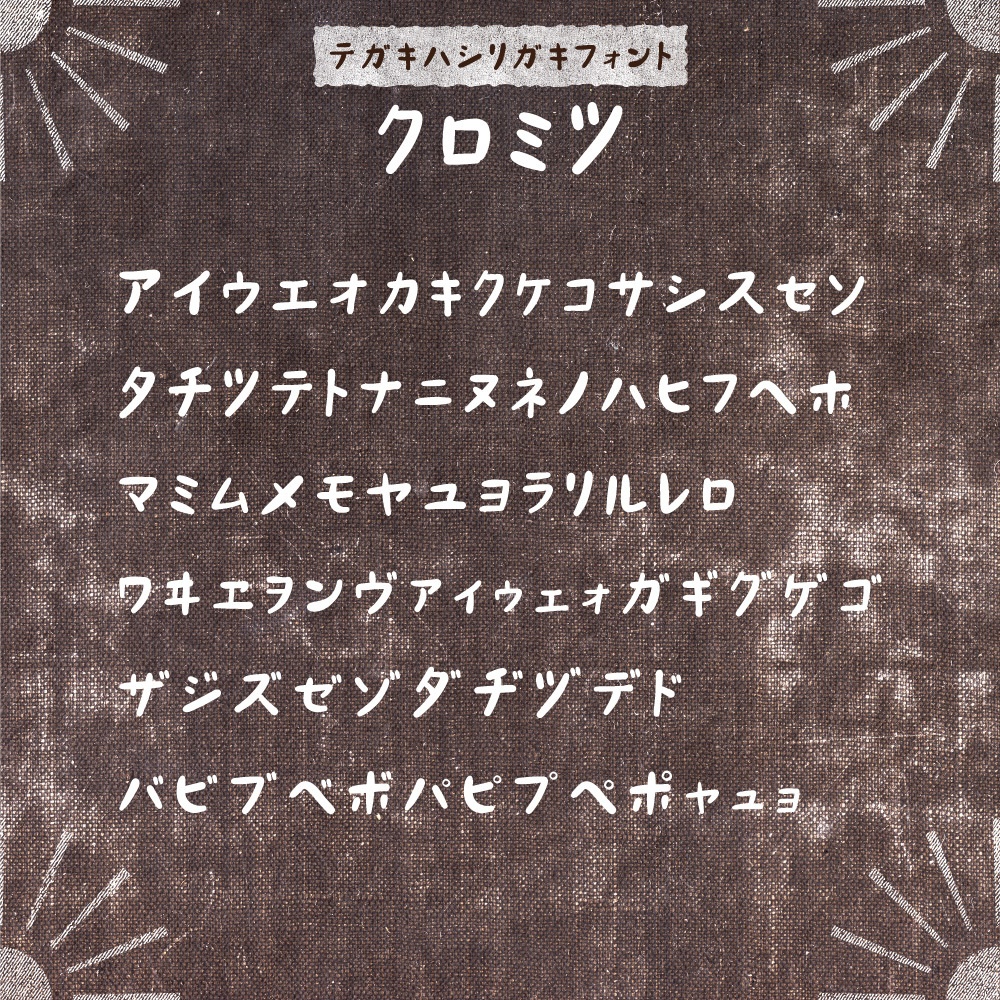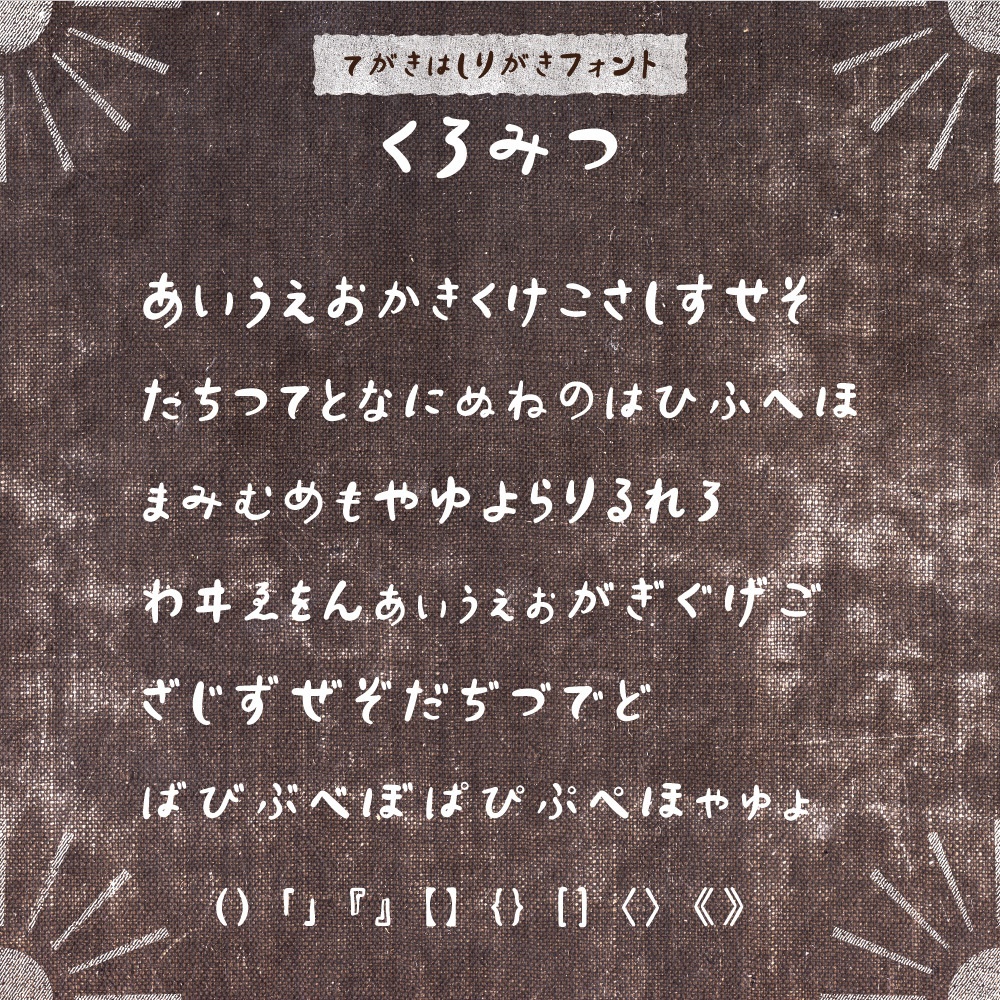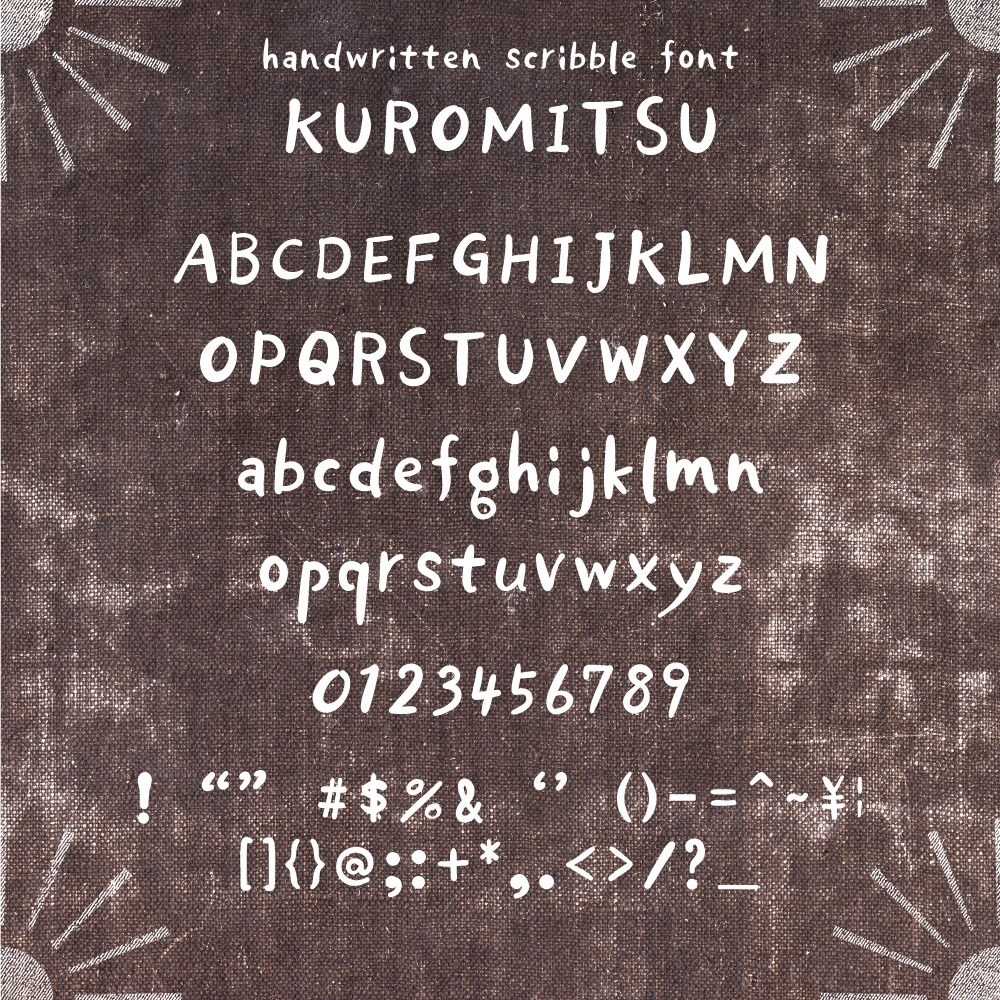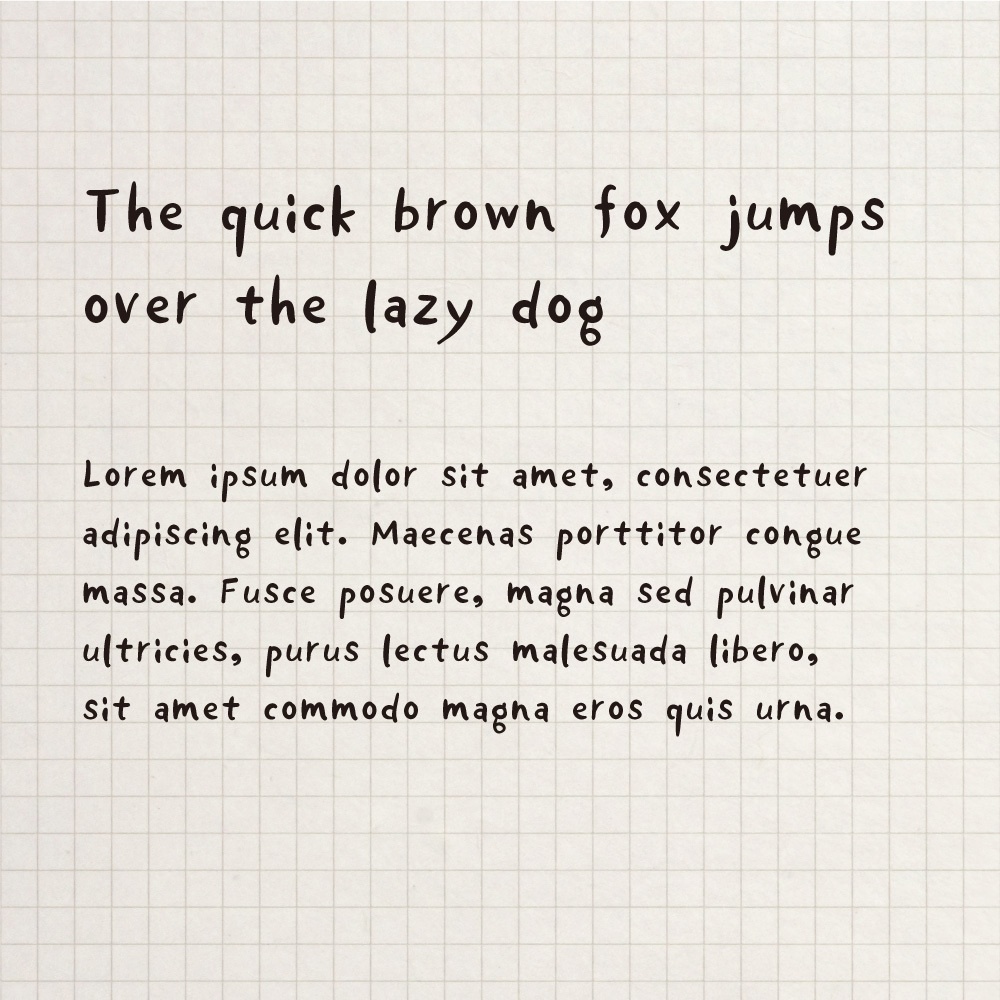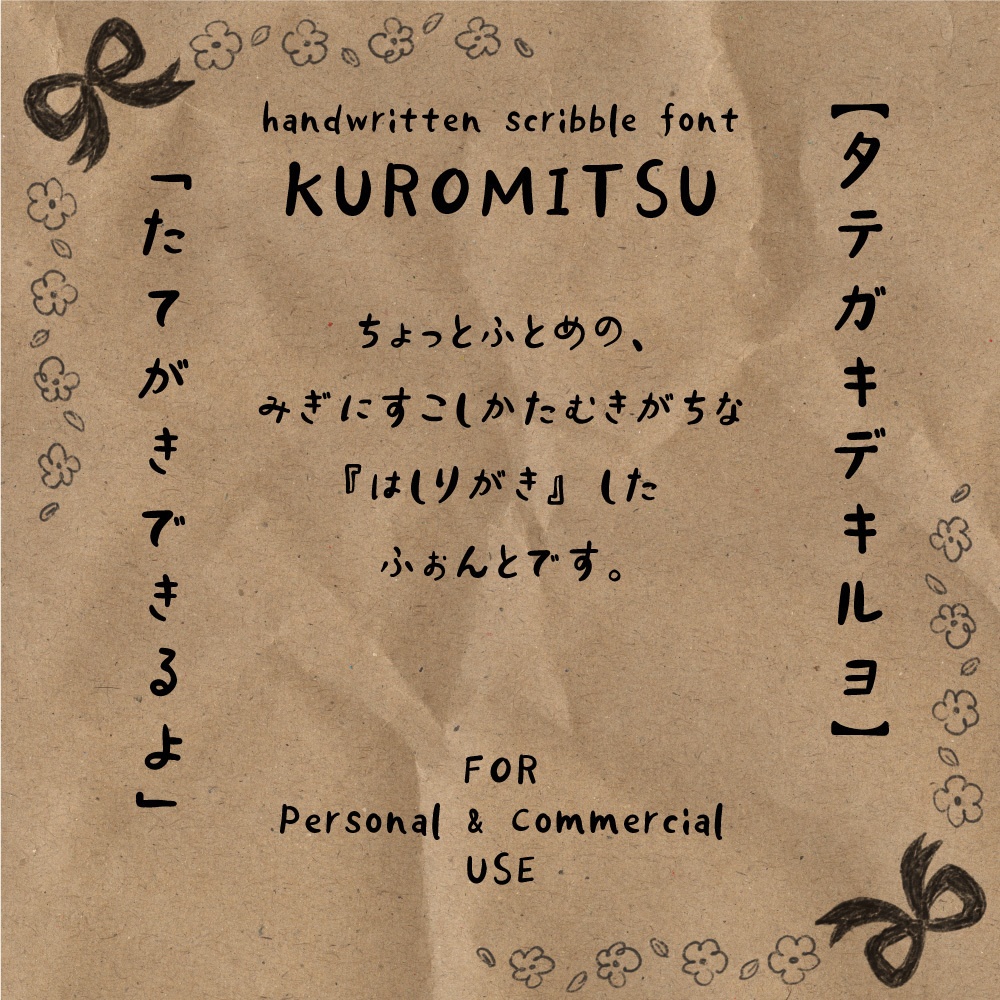
【商用可/縦書き対応】黒蜜 くろみつ ひらがな・カタカナ | 味のあるかわいいへた字 KUROMITSU
【商用可・縦書き対応】黒蜜 くろみつ ひらがな・カタカナ | 味のあるかわいいへた字 KUROMITSU ひらがな・カタカナ・アルファベット・記号を収録した、味のあるかわいい日本語フォントです。 同人誌・SNS・動画・WEBデザインなど幅広い用途にお使いいただけます。 右にちょっぴり傾きがちな走り書きフォントです。 商用利用OKです。 ひらがな・カタカナ・アルファベット・記号 収録 フォント形式:OpenTypeフォント 【動作環境】Windows / Mac 対応 【インストール方法】 Windows:ダウンロードしたZIPを解凍し、.otfファイルを右クリック→「インストール」 Mac:Font Bookにファイルをドラッグ&ドロップ ▼ まず試してみたい方へ ・無料お試し版(英数字・記号のみ)→ https://vanillabeanz.booth.pm/items/5965979 ・常用漢字版(¥3,490)→ https://vanillabeanz.booth.pm/items/6170637 【ご注意】 クロミツ「アルファベット版(Free)」「ひらがなカタカナ版」に収録されたものと『常用漢字』版に収録されたものとは異なりますので、予めご了承ください。 【ご利用条件について】 ・個人・商用利用ともにご利用可能です。 ・ご利用にあたってクレジット表記の必要はありません。 ・フォントの著作権は、放棄しておりません。 ・ご使用によるトラブルや損害等、一切の責任を負いませんのでご了承ください。 下記の事項でご利用いただけます。 1. WEB・印刷物・動画へのデザインに使用 2. ソーシャルメディア、電子書籍への使用 3. ロゴへの使用(商標登録は不可) (※ご不明な場合は、お問い合わせください。) 4.LINEスタンプへの使用 ※イラスト等のセリフへの使用可能 フォントがメインキャラクターにならない場合のみ使用可能です。 下記の事項でのご利用は不可とさせていただきます。 1. フォントデータの販売 2. フォントデータの再配布 3. 商標登録 4. 公序良俗に反するものへの利用